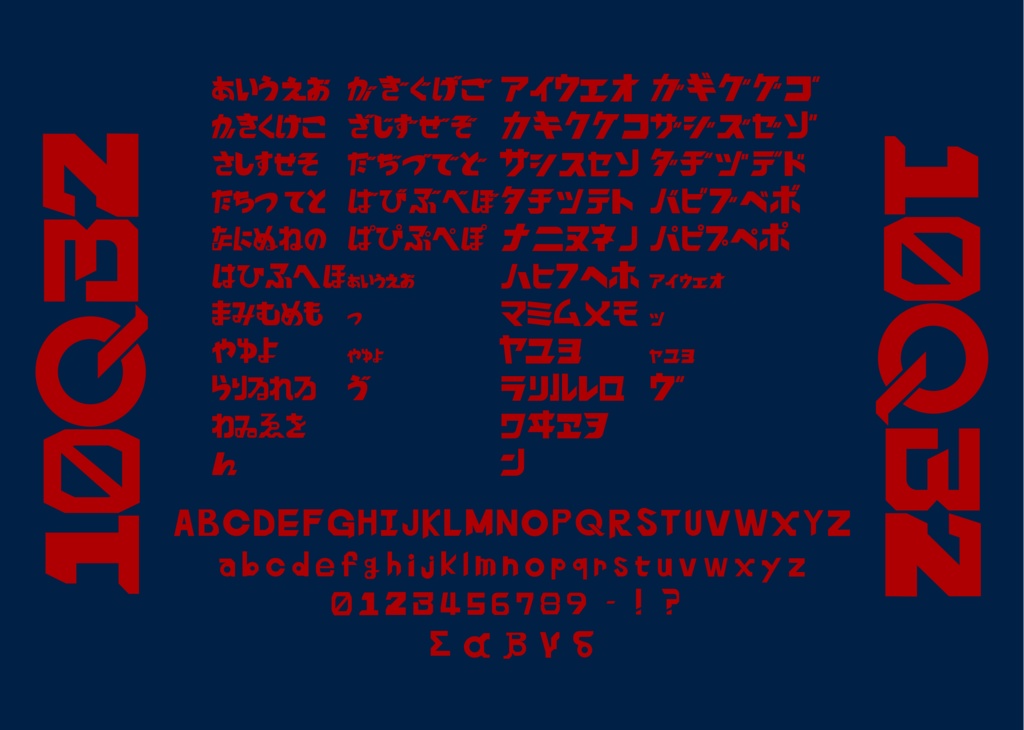
オリジナルフォント「10Q32」
オリジナルフォントの新作、10Q32は特撮をテーマにした和文フォントです。 https://x.com/chieshino のフォローで商用利用が可能となります。 以下の利用規約に基づいてご利用ください。 ・予告なく利用規約は追加・変更することがあります。あらかじめご了承ください。 ・製作者 ちえしの ねおんのTwitterアカウントをフォローすることで商用利用が可能になります。(https://twitter.com/chieshino ) フォローしない場合は基本的に利益の発生しない個人利用の範囲内であればご自由にお使いいただけます。 ・当書体データそのもの、改変した書体を再頒布することを禁じます。 ・当書体を用いて制作したロゴデザインなどの意匠に知的財産権の登録をする際はご連絡ください。 ・著作権はすべて製作者に帰属します。 ・当書体を使用して生じたいかなる損害につきましても当方は一切の責任を負わないものとします。